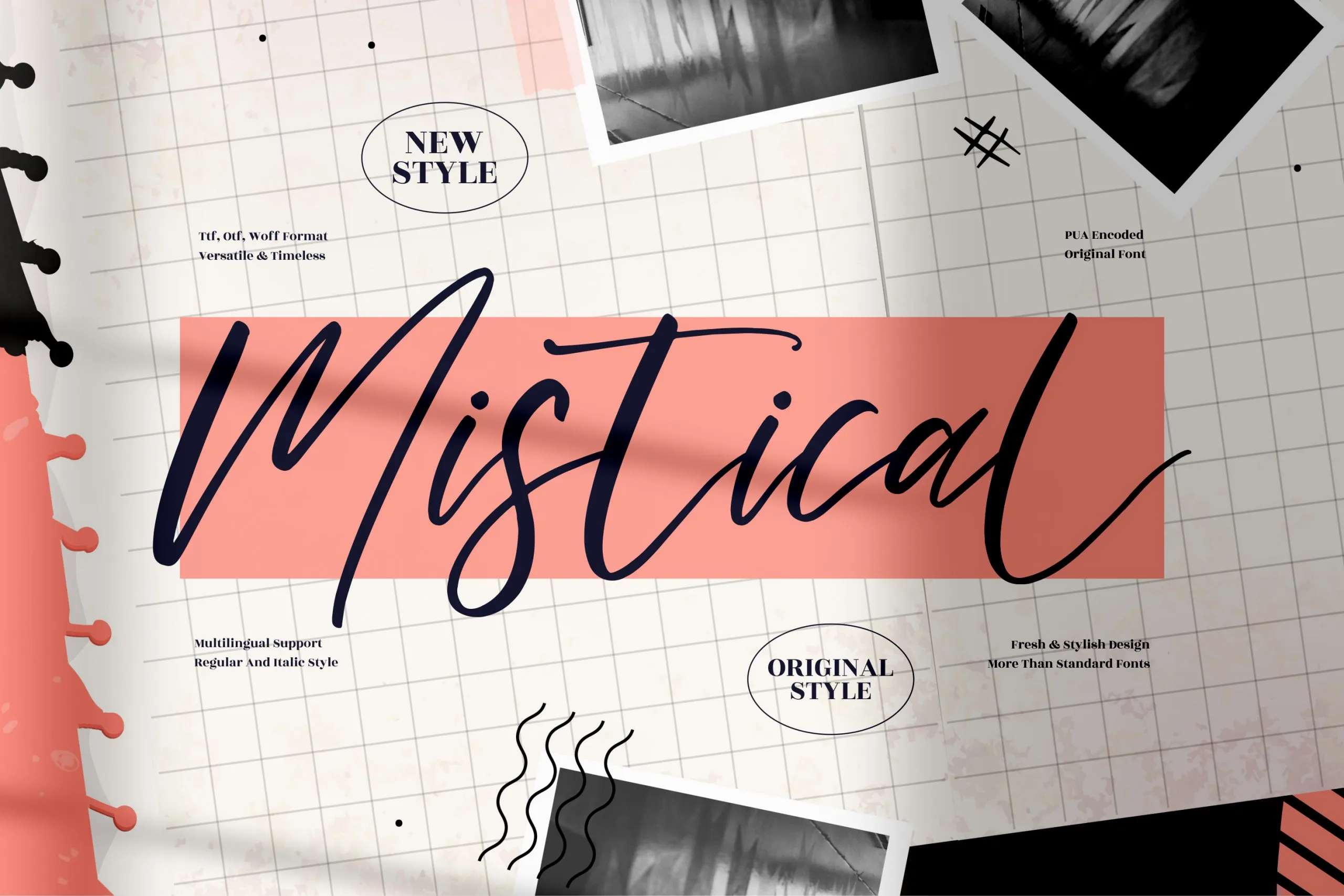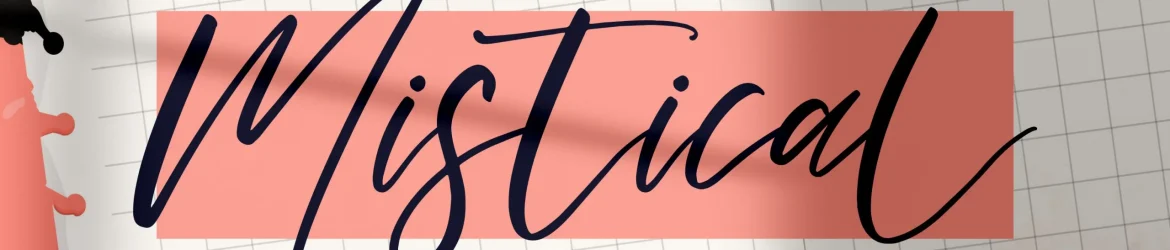
Mistical Font – Download Grátis
Esta é uma fonte escrita a mão perfeita para projetos variados que precisam de um toque elegante e pessoal. Ela se adequa perfeitamente a criações como logotipos, projetos de marca, designs de móveis de casa, embalagens de produtos, talheres, cartões de mensagens, camisetas personalizadas, capas de livros, cartões de nome, cartões de convite, cartões de presentes, etiquetas e até mesmo para imagens e marcas d’água. Ela também é perfeita para o seu próximo projeto exclusivo que precise de uma pitada de escrita a mão única. Combinada ao design cuidadosamente elaborado do designer perspectype, ela oferece um toque autêntico e sofisticado às suas criações. Independente da natureza do seu trabalho, esta fonte escrita a mão irá lhe dar o resultado perfeito para destacar sua obra no meio dos demais. Sua facilidade de uso, combinada com sua incrível expressividade, torna esta fonte um investimento valioso e uma escolha segura para qualquer profissional ou amante da design que busca qualidade e consistência em seus trabalhos.